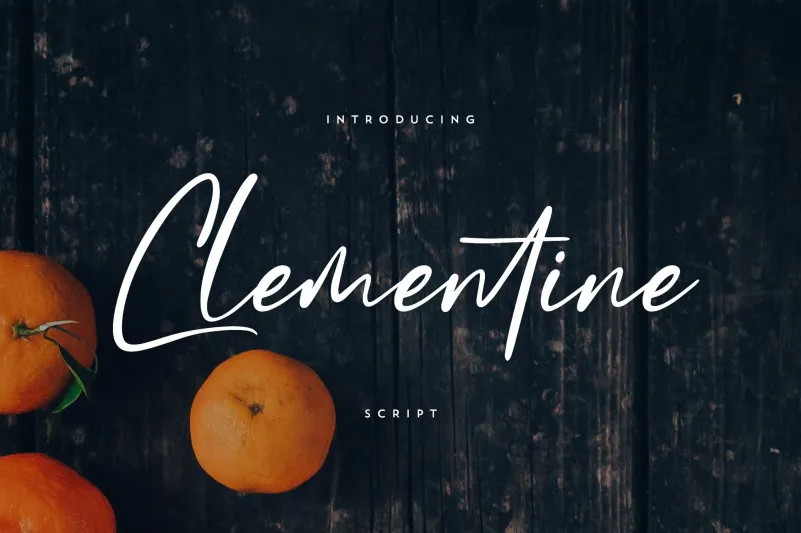
Clementine Script Font é uma elegante escolha para quem busca uma tipografia script limpa com suporte a múltiplas línguas. Essa fonte oferece uma grande versatilidade, adaptando-se bem tanto nos tamanhos grandes quanto nos menores. Se você está procurando por uma opção de fontes que combina estilo sofisticado com fácil utilização em vários contextos, Clementine Script Font é uma excelente escolha. Com seu design limpo e seu suporte a múltiplas línguas, ela torna o processo de design um pouco mais divertido e versátil. Ideal para aplicativos de texto e websites, esta fonte se destaca como uma opção criativa e funcional que é fácil de usar em qualquer projeto gráfico.